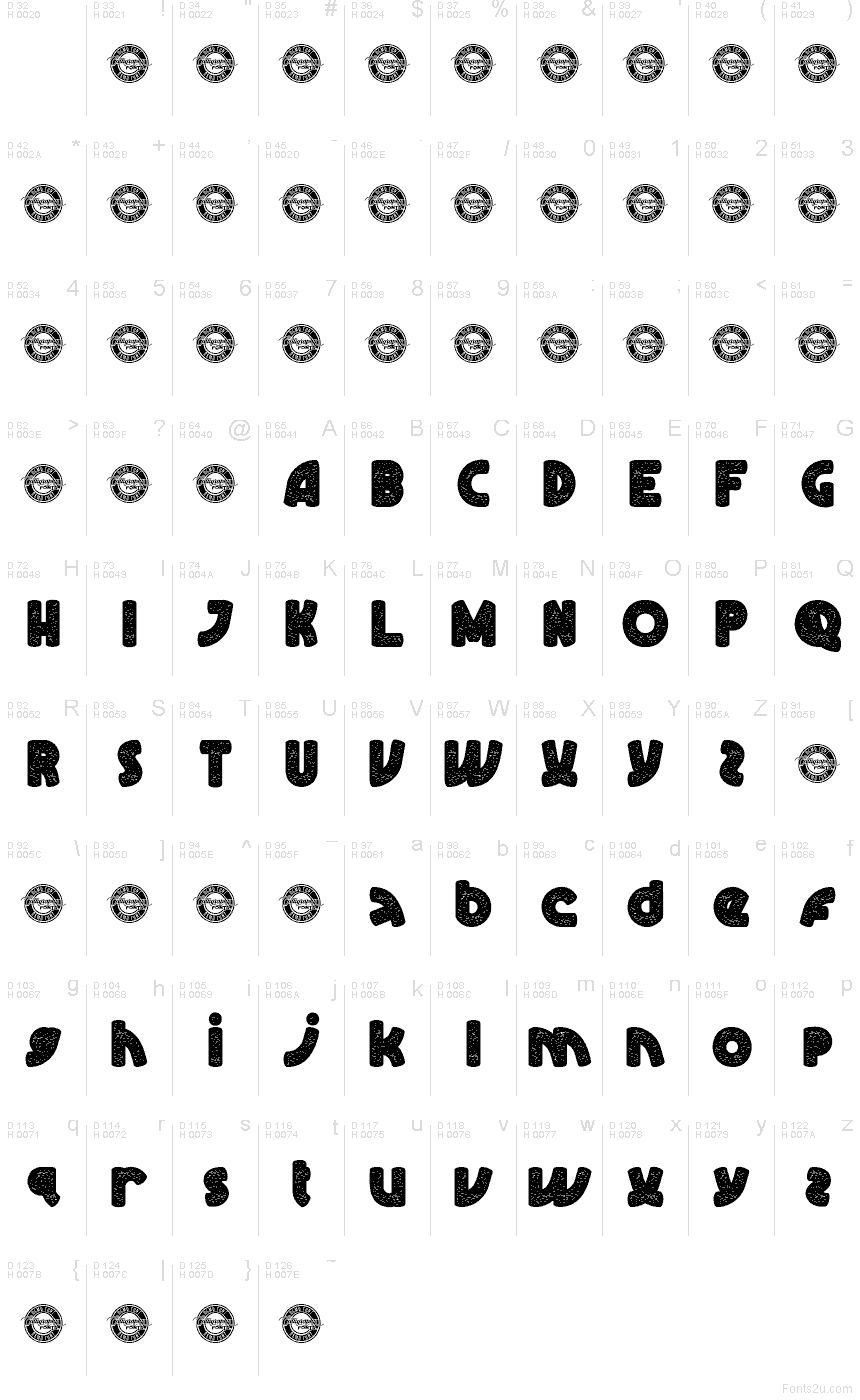
DoodleChalkDemo
Doodle Chalk od CalligraphyFonts.net je bezplatné písmo v štýle kriedovej tabule. Jeho hrubé, zaoblené tvary sú plné bielych škrabancov, ktoré imitujú kriedu na tmavej ploche. Táto textúra tvorí základ jeho štýlu a dodáva písmenám školskú atmosféru, zatiaľ čo jemné tvary zabezpečujú, že písmo nepôsobí roztrapkano alebo špinavo.
Ideálne sa hodí na školské plagáty, tabule s menu v kaviarňach, detské pozvánky, ručne vyrábané etikety či nadpisy do albumov, kde táto kriedová plocha sama o sebe funguje ako dekorácia. Najlepšie vynikne v krátkych nadpisoch a nápisoch, pretože široké tvary písmen poskytujú dostatok priestoru na to, aby bol efekt opotrebovaného povrchu dobre viditeľný.